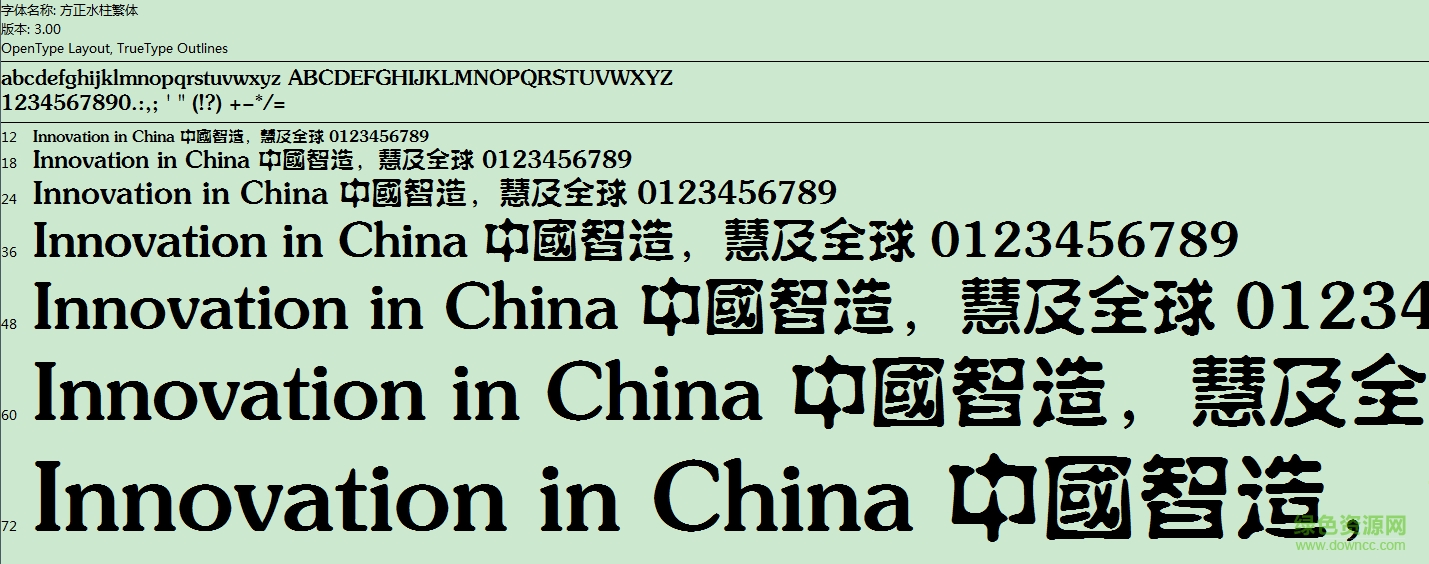
fzszfw gb1 0字体是一款字形端正的方正字体,这款字体笔画之间具有一定的间隙,形似水柱断裂了一般,但是整体效果会特色的出彩,喜欢的朋友欢迎下载使用!
fzszfw gb1 0字体简介
fzszfw gb1 0字体是什么字体?它就是我们常见的方正水柱繁体字体,是一款根据非诚有趣的黑体字体,这款自最大的特色的有些笔画之间并不是相连的,整体看上去非常顺眼!